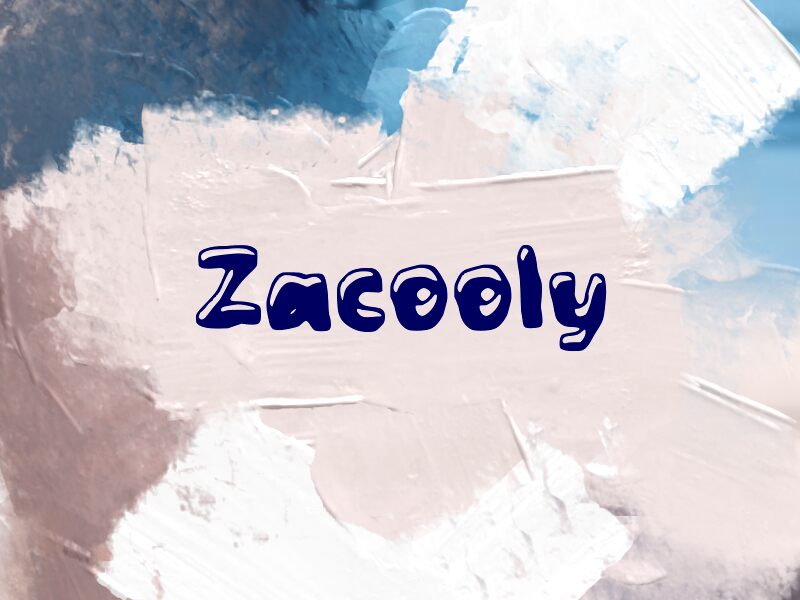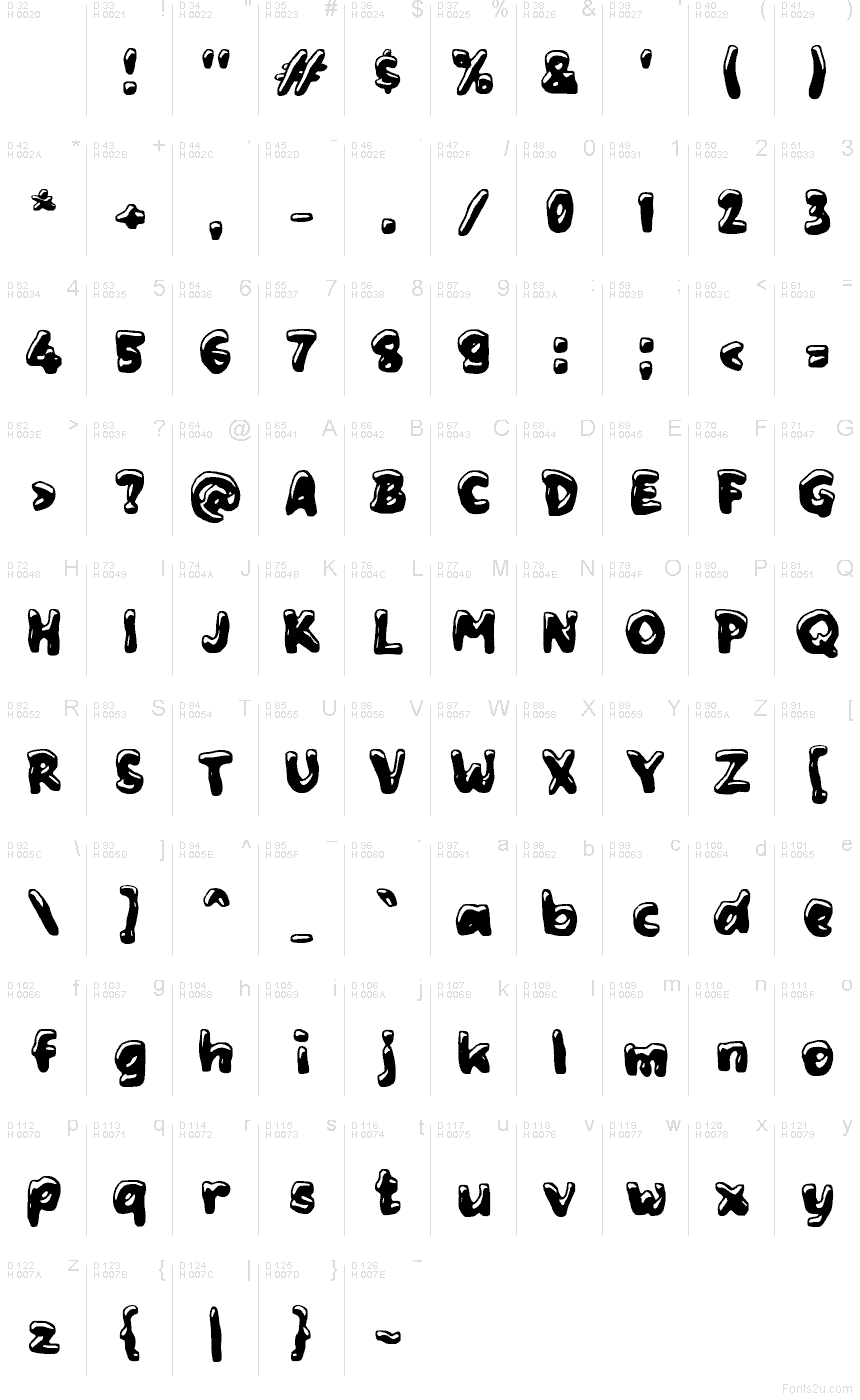
Zacooly par Wep est une police d'affichage gratuite de type « bulle de cartoon », au rendu doux et fondant, avec un rythme trapu et ludique. Les lettres semblent plutôt versées que dessinées, avec des bords arrondis, des formes gonflées et des reflets éclatants qui donnent à cette police un aspect brillant et gourmand.
Elle est parfaite lorsque vous voulez que vos mots courts dégagent une ambiance légère et un peu loufoque : packagings pour enfants, branding de snacks, flyers de fête, autocollants, titres YouTube ou gros titres d'affiches informelles. En tant que police gratuite, Zacooly fonctionne particulièrement bien pour les logos, les couvertures et les visuels rapides pour les réseaux sociaux, car ses lettres rebondies imposent le ton avant même d'ajouter quoi que ce soit d'autre.
Zacooly
Présentation et spécimen de la police Zacooly